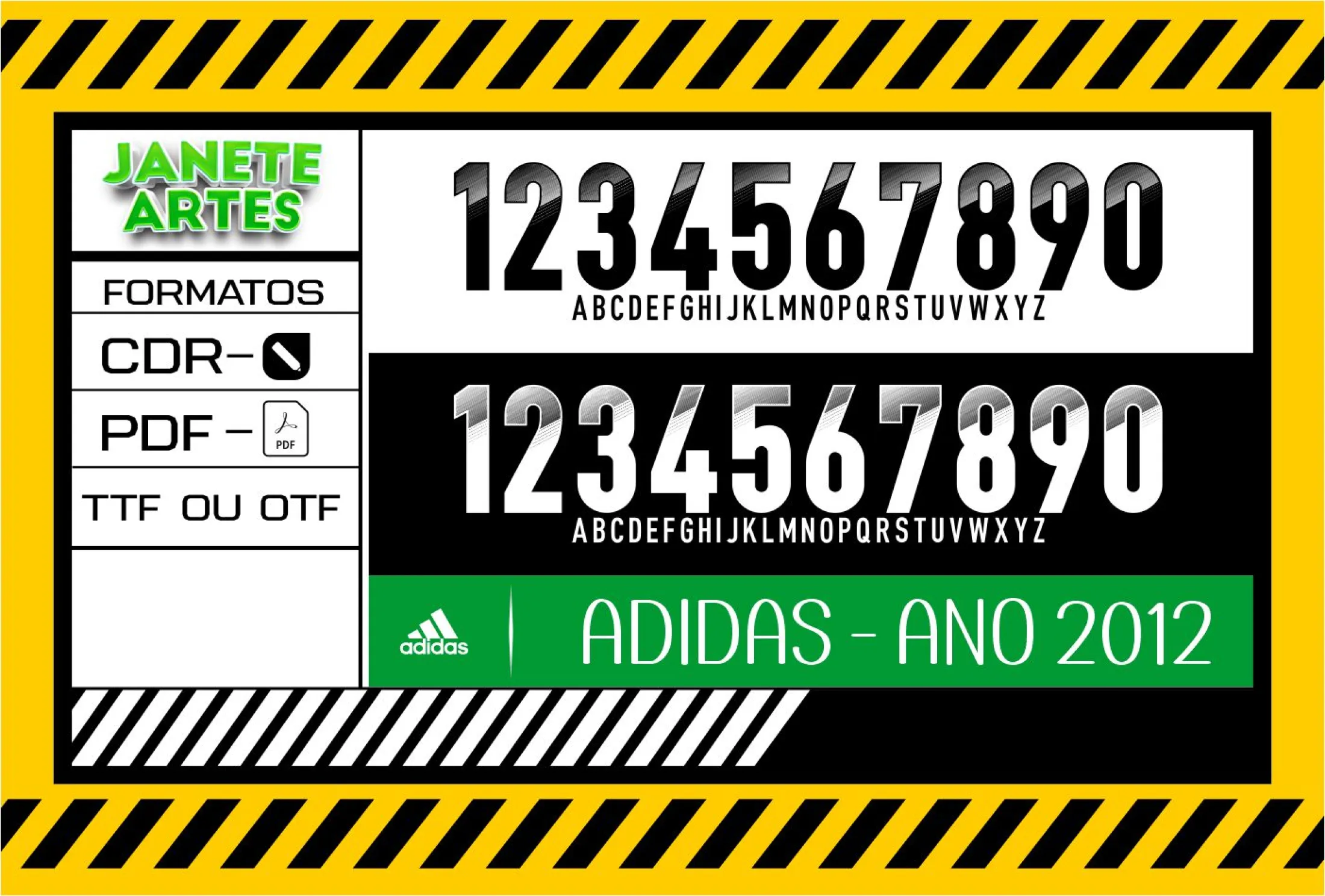
Fonte de Time Tipografia Adidas 2012
Baixe agora a Fonte de Time Tipografia Adidas 2012 e personalize suas camisetas com um design único e cheio de estilo, perfeito para times, fãs e eventos esportivos.
Uma história de paixão e estilo no futebol ⚽️
Imagine-se naquela tarde de domingo, com os amigos na arquibancada, todos vestindo camisetas que representam seu amor pelo time e sua paixão pela adidas. Foi assim que nasceu a inspiração para a Arte Fonte de Time Tipografia Adidas 2012 para Camisetas. Um design que revive o estilo icônico de 2012, trazendo a energia daquele ano memorável para o seu guarda-roupa. Entre risadas, emoções e gols decisivos, essa fonte marcou presença, deixando cada fã com um motivo a mais para vestir a camisa do seu time.
Com o Arte Fonte de Time Tipografia Adidas 2012 para Camisetas você traz para suas peças um toque único e cheio de personalidade. Personalize, vista e mostre seu orgulho pelo futebol e pela marca que marcou época! 👕🔥